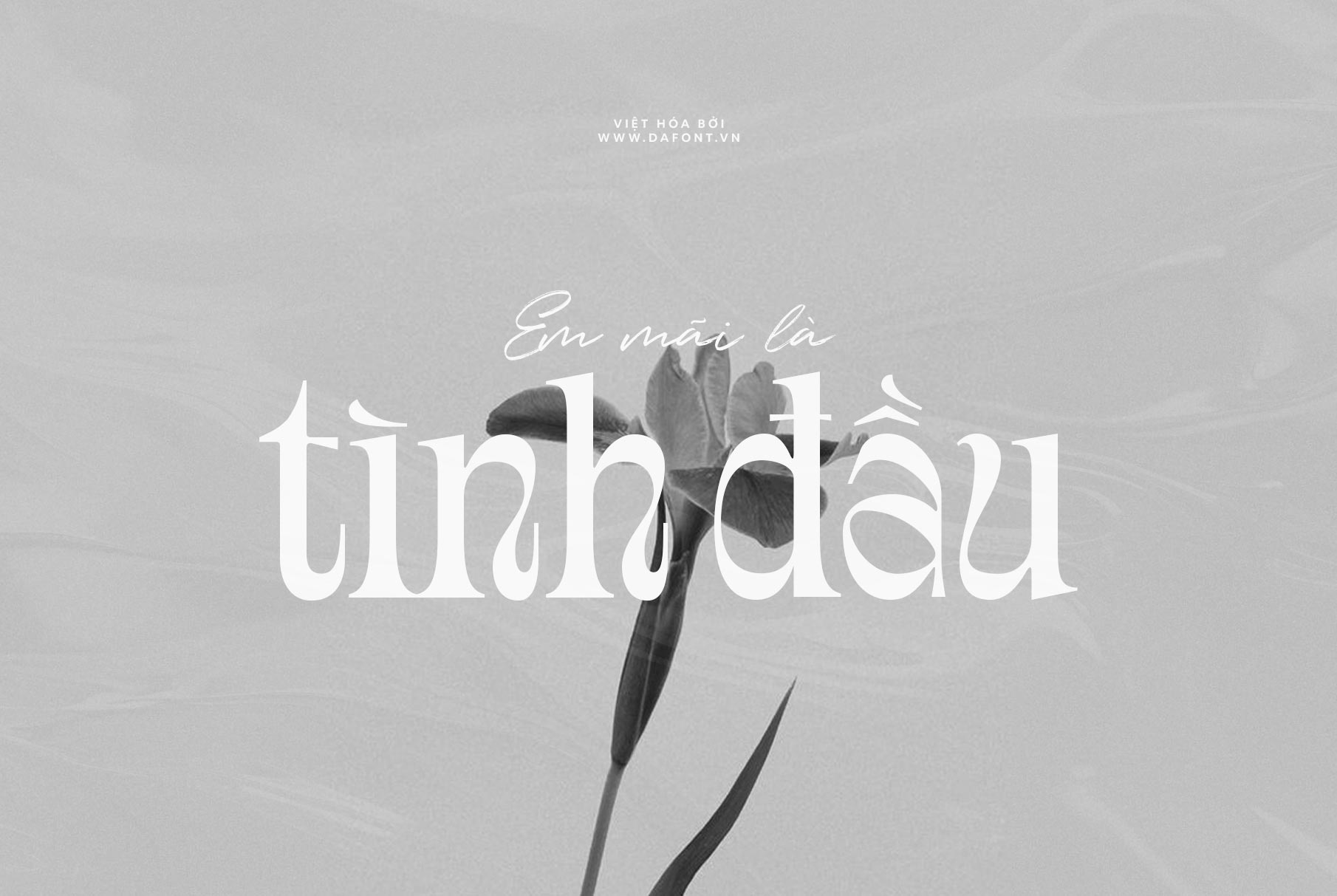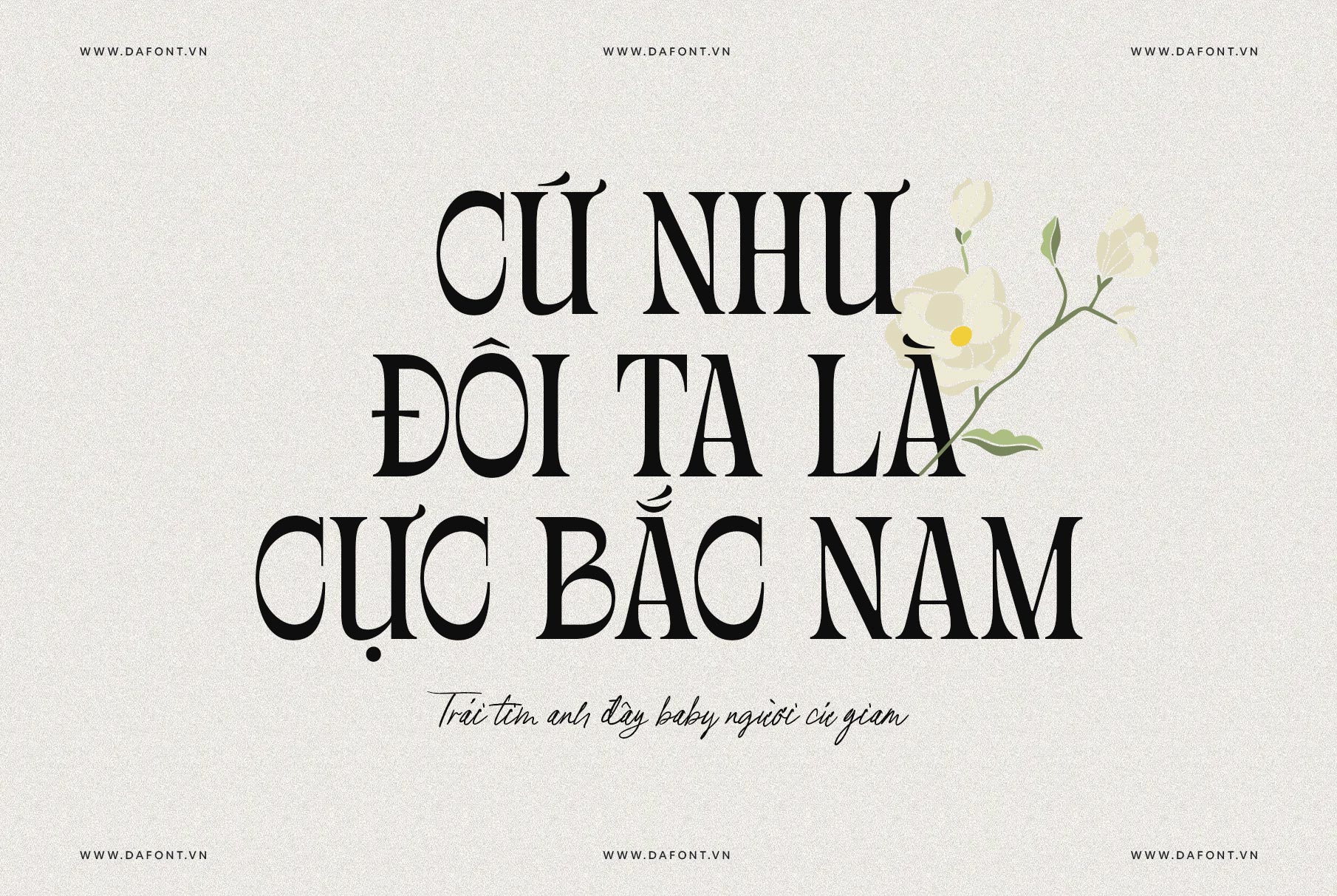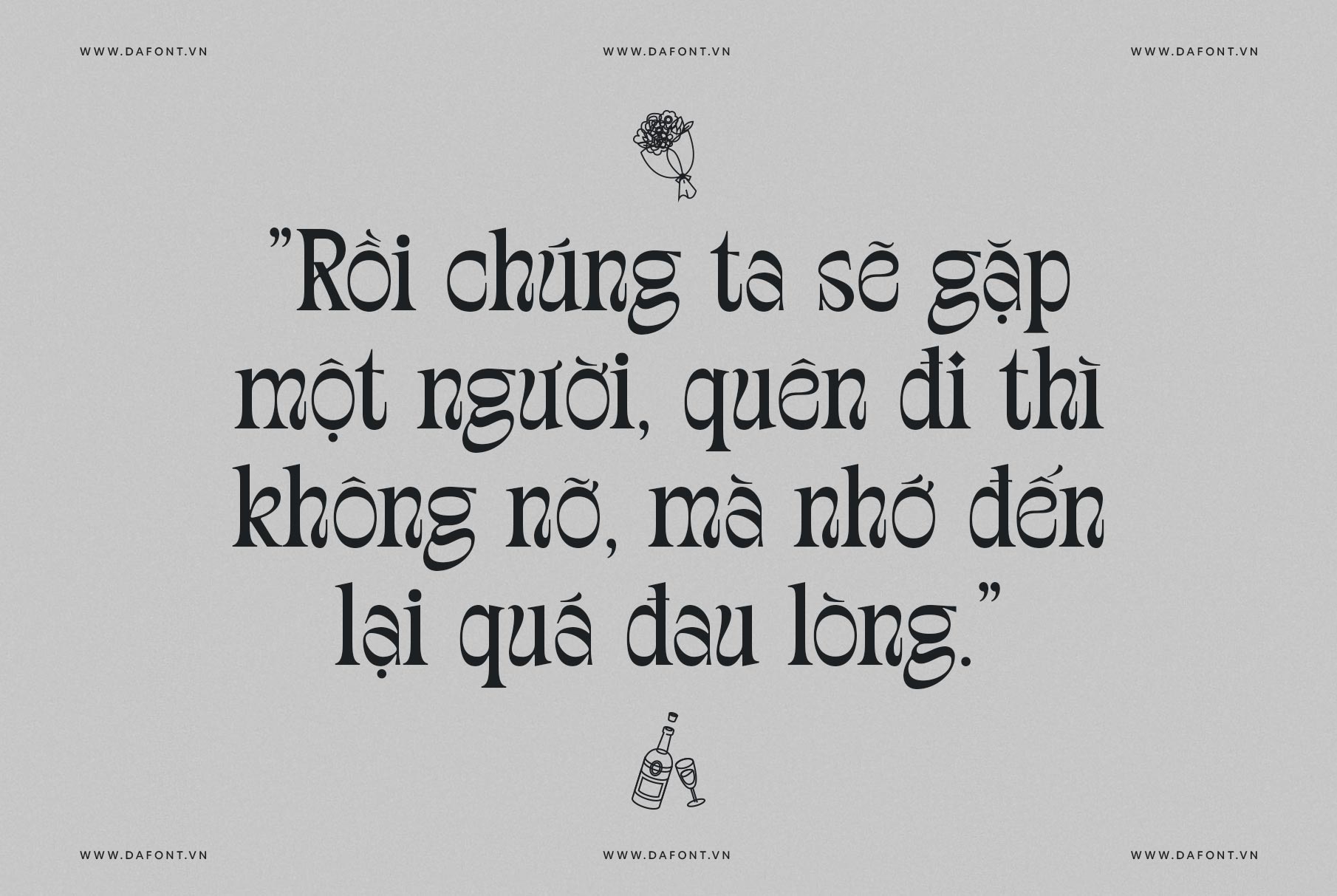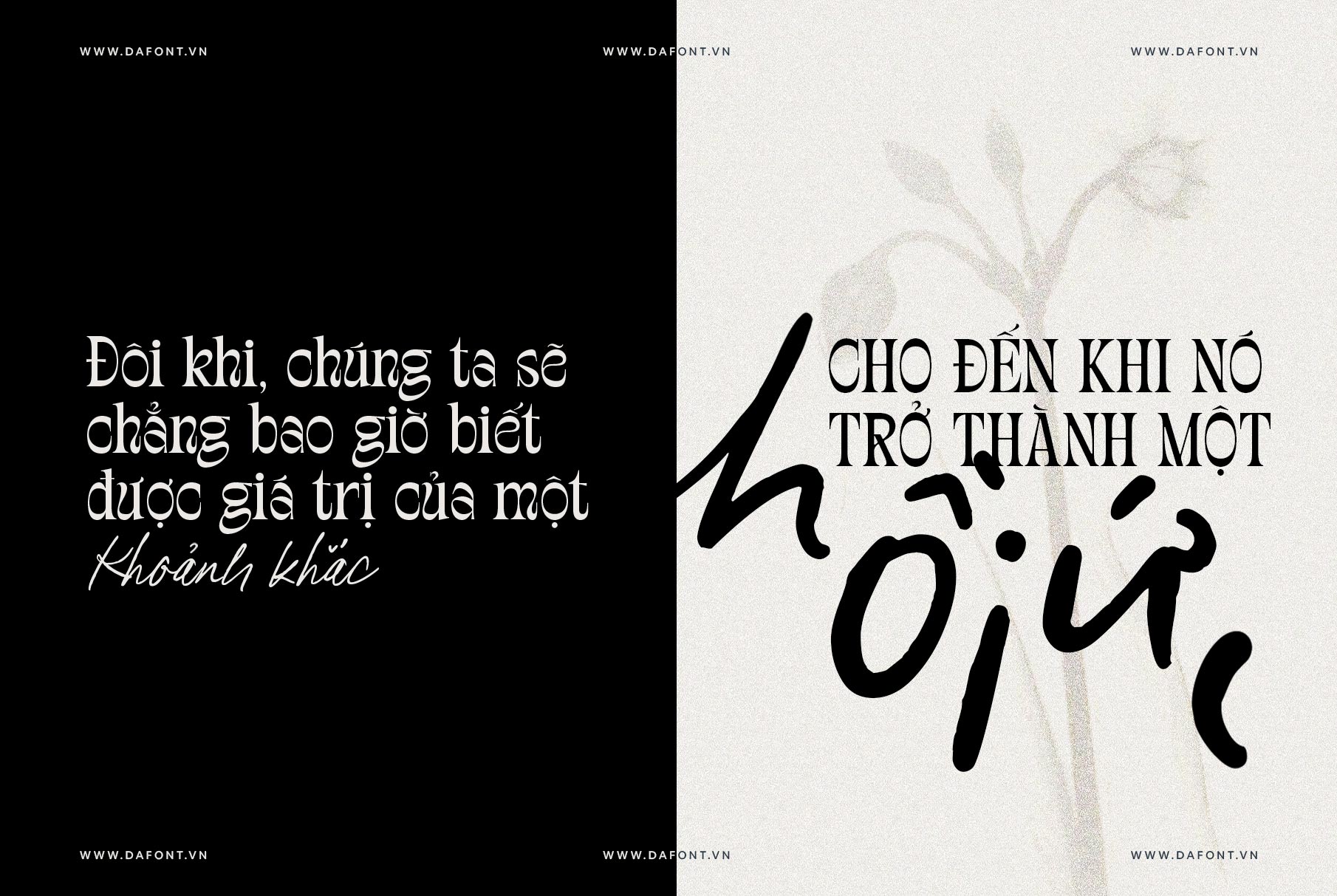
TAN – FAIRGROUNDS là một font chữ serif cổ điển với một chút biến tấu hiện đại, tạo nên sự độc đáo trong từng nét chữ. Tan Fairgrounds không chỉ mang đến sự thanh lịch, mà còn truyền tải cảm giác vui vẻ và sáng tạo, giúp các dự án thiết kế trở nên nổi bật và dễ nhớ hơn. Với thiết kế mềm mại và lôi cuốn, font Fairgrounds không chỉ dễ đọc mà còn giúp các dự án thiết kế trở nên nổi bật, phù hợp cho nhiều ứng dụng như logo, tiêu đề, poster và bao bì sản phẩm.
Đặc điểm nổi bật TAN – FAIRGROUNDS
- Phong cách sáng tạo: Tan Fairgrounds có thiết kế dựa trên kiểu chữ serif cổ điển nhưng được cách điệu để mang lại cảm giác hiện đại, tươi mới và thu hút.
- Tính linh hoạt cao: Font chữ này phù hợp cho nhiều loại dự án khác nhau, từ thiết kế bao bì, tiêu đề báo chí, thiệp mời, poster, cho đến các ấn phẩm quảng cáo.
- Hỗ trợ đa ngôn ngữ: Với tính năng hỗ trợ đa ngôn ngữ, Tan Fairgrounds dễ dàng sử dụng trong các dự án quốc tế mà không gặp khó khăn về ký tự.
Lý do bạn nên chọn TAN – FAIRGROUNDS
Tan Fairgrounds Font không chỉ là một công cụ hỗ trợ thiết kế mà còn là một yếu tố giúp xây dựng phong cách riêng, tạo cảm giác gần gũi và mới lạ. Nếu bạn muốn làm nổi bật dự án của mình với một font chữ độc đáo, sáng tạo và có tính ứng dụng cao, Tan Fairgrounds chắc chắn là lựa chọn đáng cân nhắc.
TAN – FAIRGROUNDS được việt hóa đầy đủ, kering lại hoàn toàn tất cả các ký tự do ban đầu font gốc chưa được kerning, ngoài ra cũng được tối ưu hóa lại các dấu.